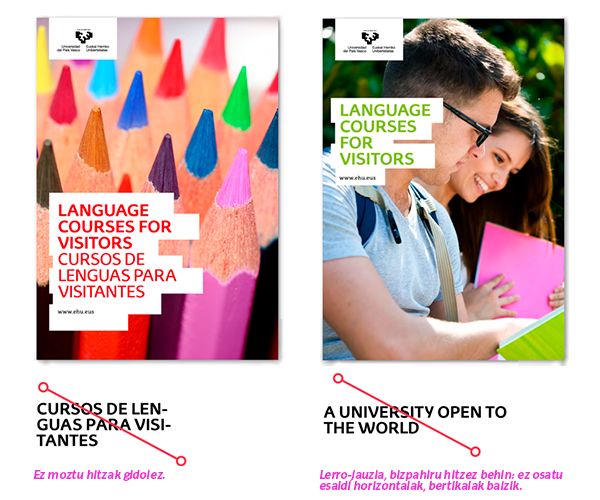
Testua eta tipografia
UPV/EHU sistema grafikoak estilo jakin bat du atxikita.
Unibertsitatera sarbideko liburuxkaren azala
Idazteko moduak zehazten du gure estiloa. Horregatik, testua eta hura idazteko modua funtsezko alderdiak dira sistema grafikoetan, estilo bisual jakin bat taxutzen eta komunikazio zuzen eta koherentea ahalbidetzen duten heinean.
Konposizioaren informazio-iturri zuzenekoena testua denez, ongi zaindu behar dugu gure mezuak komunikatzeko era.
EHU tipografia korporatiboa erabiliko dugu komunikazio-material guztietan, hurrengo orrialdeetan adierazten den moduan.
Tipografia
EHU tipografia: EHUSerif eta EHUSans
Gure tipografia nagusia
UPV/EHUko tipografoen taldeak diseinatutako EHU letra-tipoen familia da gure molde korporatiboa. Tipografia hori berariaz diseinatu dute UPV/EHU markaren adierazpide berri honetarako. Bi bertsio ditu (Serif eta Sans). Bertsio bakoitzak hiru pisu ditu —Bold, Regular eta Serif—, diseinu-elementu bakoitza behar bezala prestatu ahal izateko.
Arial tipografia
Ordezko tipografia
Bitarteko digitaletarako, Arial tipografia erabil daiteke; bereziki, ordenagailuetan gure tipologia instalatuta ez duten hirugarrenek aplikazioren bat ikusi eta partekatu behar badute. Garrantzizko oharra: Ez erabili ordezko tipografiarik aplikazio profesionaletan edo komunikazio-euskarri inprimatuetan.
Izenburuen konposizioa
Bi azalen adibidea
Gure sisteman, estilo hauxe erabiltzen dugu: azaletako testuak lantzeko, informaziopieza nagusiak eta testuen izenburuak, oro har, espaziokutxaren barruan idazten dira, tarte zabal eta irregular batek inguratuta, ezkerrean lerrokatuta eta hitzak gidoiez moztu gabe.
Izenburua letra larriz idatziko da, eta laburra behar du izan, 7-8 hitz, gutxi gorabehera. 7-8 hitzetik gora dituenean, proportzioan txikituko da testuaren tamaina.
Baliteke izenburu batzuk lerro bakarrean sartzeko modua izatea, baina konposizioagatik eta diseinuagatik, hizkuntza bakoitzeko izenburua lerrotan zatituko da, bost lerrotan gehienez ere, bizpahiru hitzez behin lerro-jauzia sartuta, ahal izanez gero.
Izenburu nagusien neurria
Titularren bi adibide, lehenengoa luzera egokikoa eta bigarrena gehiegizko luzerakoa
Gehienez ere 7-8 hitz dituzten izenburuak erabiltzea gomendatzen da, barne direla gaztelaniazko artikuluak eta preposizioak. Ez da komeni proportzio horretatik gorako izenbururik idaztea, lehia bisuala sortuko baita mezua ilustratzen duen baliabide bisualarekin.
Kutxa altua eta kutxa baxua
Izenburuentzako kutxa altua eta testurako kutxa baxua nola erabili erakusten duen adibidea
Kutxa altua erabiliko dugu izenburu nagusietarako, eta kutxa baxua, bigarren mailako edukia duten testuetarako (b).
Kerninga eta lerroartea
Izenburuak eta bigarren mailako izenburuak osatzeko, kontuan hartu behar da kerninga. Dokumentu elebakarrei 0 kerninga aplikatuko zaie kutxa altuan EHUSerif letraz idatzitako izenburu eta bigarren mailako izenburuei, eta -10 optikoa, eduki-testuei.
Dokumentu elebidunei edo hiru hizkuntzatan idatziei dagokienez, -25 kerning optikoa ezarriko zaie EHUSans letraz idatzitako izenburuei, bigarren hizkuntzan. Horrek emango dizkigu informazioa argi eta sendotasunez adierazteko gakoak (a) (b).
Testuen lerrokatzea, azaletan
Logotipoaren azpiko izenburuaren lerrokaduraren adibidea
Testu guztiak (azaletako izenburuak, bigarren mailako izenburuak, web-orria, informazio-testuak...) bertikalki lerrokatzen dira, ezkerrean, Unibertsitatearen logotipoarekin, ahal denean.
Dokumentu elebakarrak. Azaletako datuen tipografia
Dokumentu elebakarraren azala
EHU tipografiaren Serif bertsioa erabiliko dugu euskarazko testuetan eta EHU familiaren Sans bertsioa ataletan ager litezkeen gainontzeko erdaratarako, bai gaztelaniarako nola ingeles, frantses eta bestelako hizkuntzetarako.
Honako era honetara erabiliko ditugu bertsio bion (Serif eta Sans) pisu ezberdinak.
Bi azalek tipografiaren pisu desberdinak nola erabili erakusten dute
Dokumentu elebakarrak. Familia tipografikoaren erabilera
Diseinu desberdineko hiru portada
DIN formatu bakoitzerako neurri eta estiloen jarraibide hauek betetzea gomendatzen da. Salbuespen gisa, neurri handiagoa edo txikiagoa erabil daiteke, konposizioaren ezaugarriak direla-eta hala behar izanez gero.
Izenburua Bigarren mailako izenburua Webgunea Informazio testu orokorra Informazio testu osagarria
EHUSerif Bold EHUSerif Regular EHUSerif Bold y Regular EHUSerif Italic
A3 Tamaina: 56 pt.
Lerroartea: 56 pt.
Kerninga: 0
Aplikazio baliogabeak
Jardunbide txarren adibideak
1. Ez da erabili ondo
2. Ez erabili ez testu bertikalik ez testu okerrik.
3. Ez inguratu inolako formarik testuaz.
4. Ez sartu testurik espazio-kutxez bestelako formetan.
5. Ez distortsionatu tipografia (ez trinkotu, hedatu edo deformatu).
6. Ez aplikatu efektu bisualik tipografiari (itzalak, lausotzeak,etab.)
7. Ez erabili tipografiaren Outline bertsioa.
8. Ez erdiratu edo lerrokatu testua ezkerrean besterik.